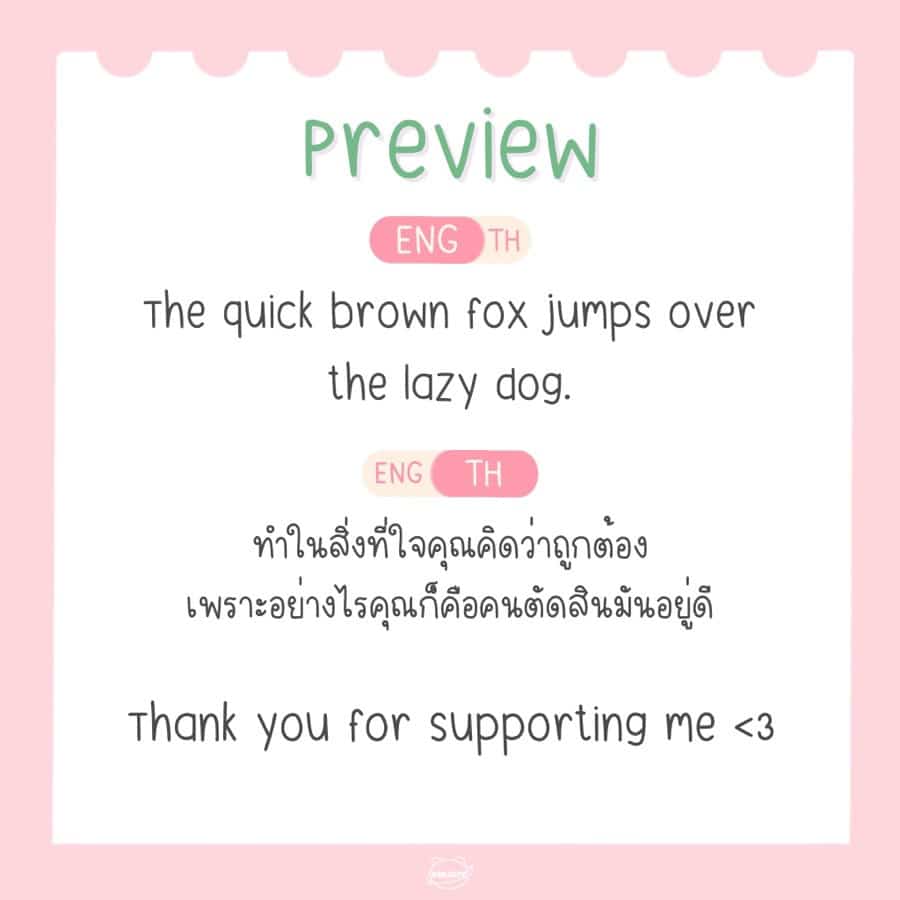
Avocado Fonts 🥑 ฟอนต์อโวคาโด✨[BBLG]
Avocado Fonts 🥑 ฟอนต์อโวคาโด✨
มาใหม่แล้วฟอนต์ลายมือแสนน่ารัก🥰 มีความเรียบร้อย ตัวบาง ใช้ทำงานดูไม่รกด้วยค้าบ💕
🖍Handwriting